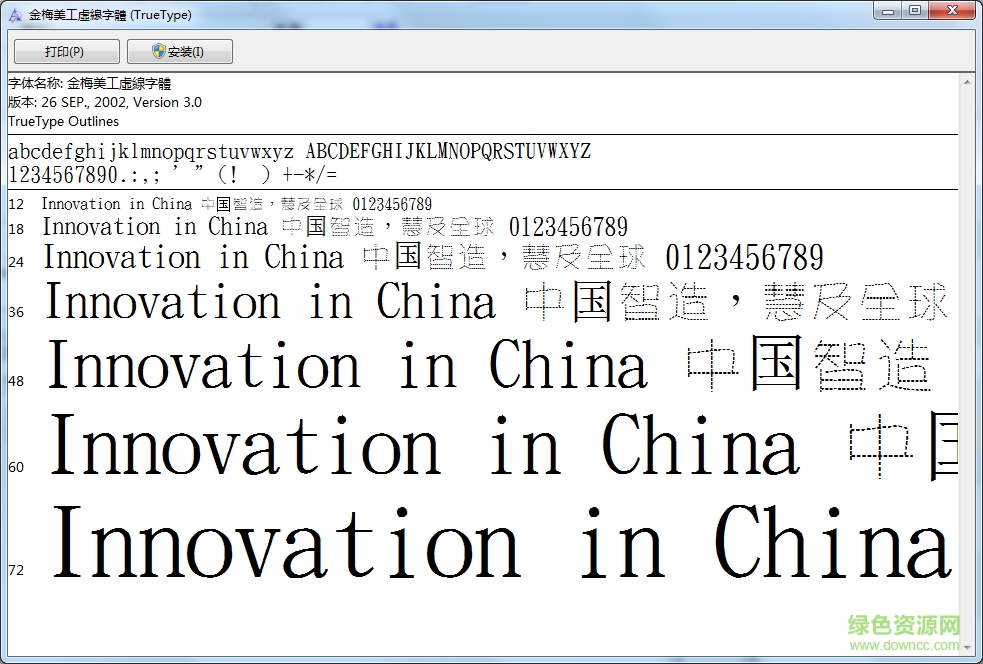
金梅美工虛線字體是一款非常精美的金梅字體,此字體主要以虛線為主,支持中英文和阿拉伯?dāng)?shù)字,漢字體現(xiàn)尤為明顯,有一種若有若無的虛幻感,對于美工的日常工作來說非常的實用,喜愛的朋友趕快到綠色資源網(wǎng)下載體驗吧!
金梅美工虛線字體由虛線構(gòu)成,字體秀美纖細(xì),美觀簡潔,本作品可用于廣告設(shè)計字體、網(wǎng)頁設(shè)計字體、包裝設(shè)計字體、屏幕顯示字體等。